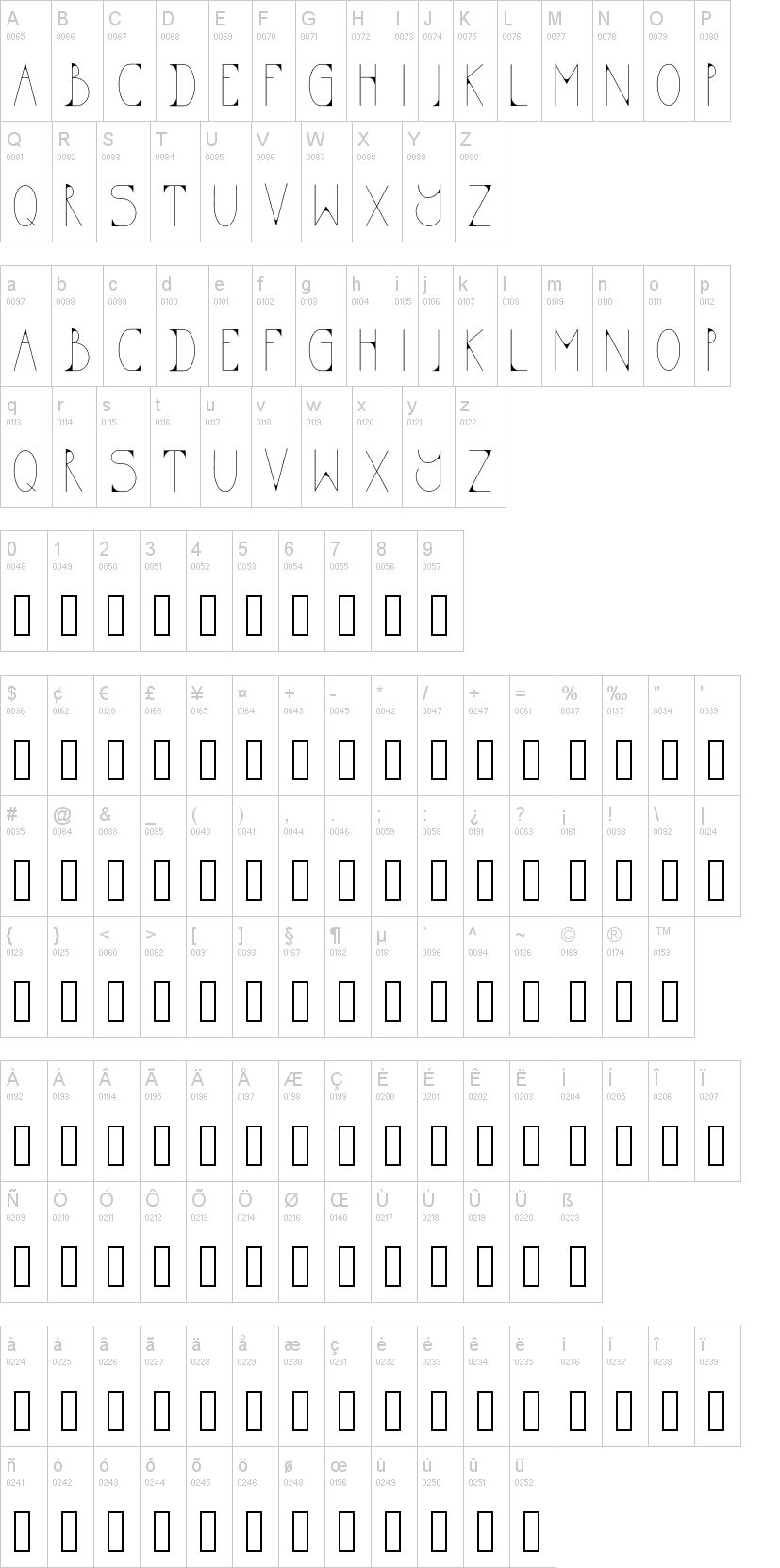
Koda
? Koda 字体是由英国设计师 Jonny Pinhorn 创建的一款现代系列字体。它的特点是简洁、灵活、精确,可以用于大多数文本类型的设计,也可以用于更复杂的头版标题或网页设计。Koda 字体的字体结构特别紧凑,用于文本的字体可以提供更多的空间,而头版标题或网页设计的字体可以提供更多的视觉效果。Koda 字体可以用于印刷品,网站,展示,广告和其它类型的设计中。
Koda是一款非常不错的手写艺术字体,具有很好的视觉感,适合于文化类的宣传设计、商业类品牌的广告和产品包装设计以及个性化文字排版等较多场景。